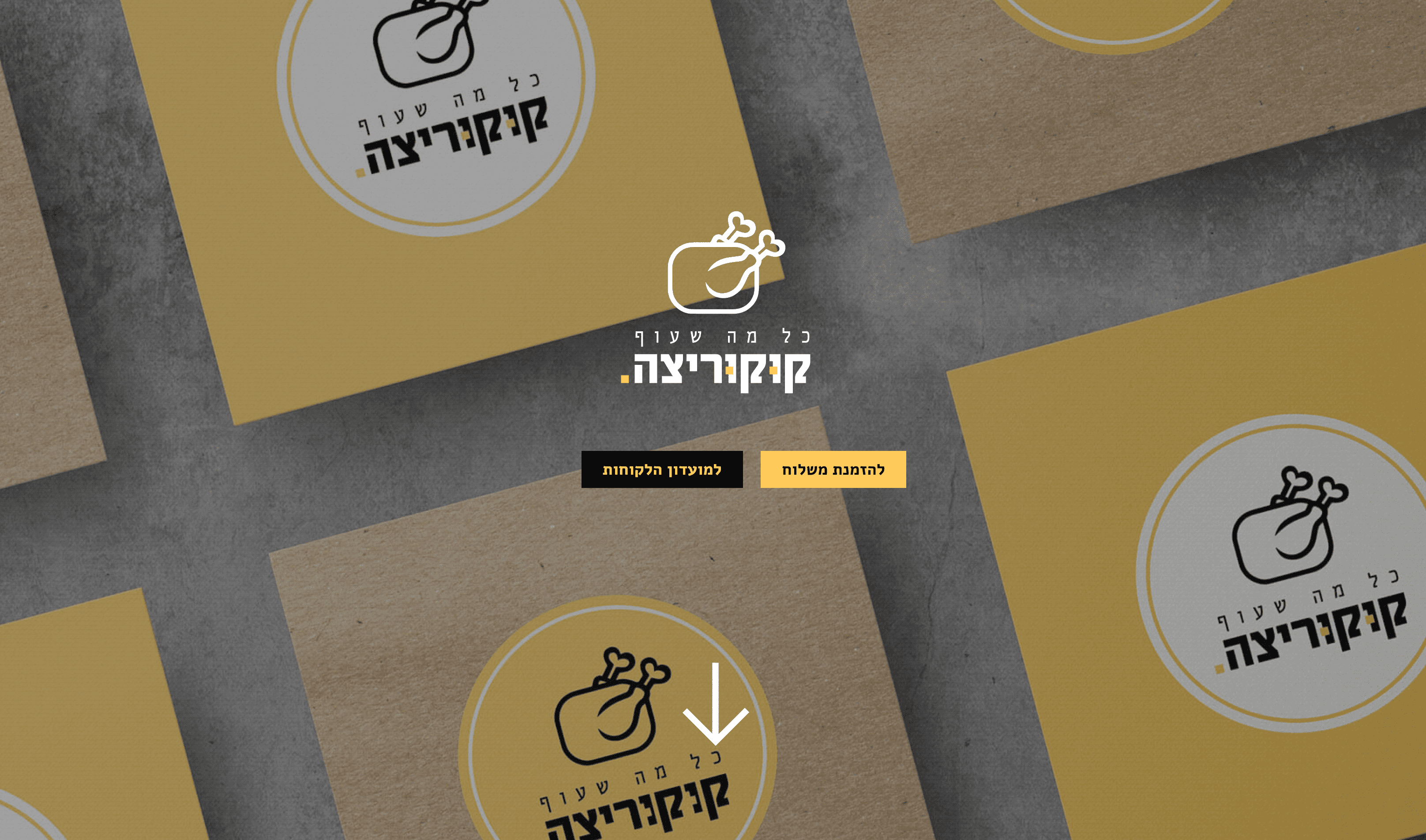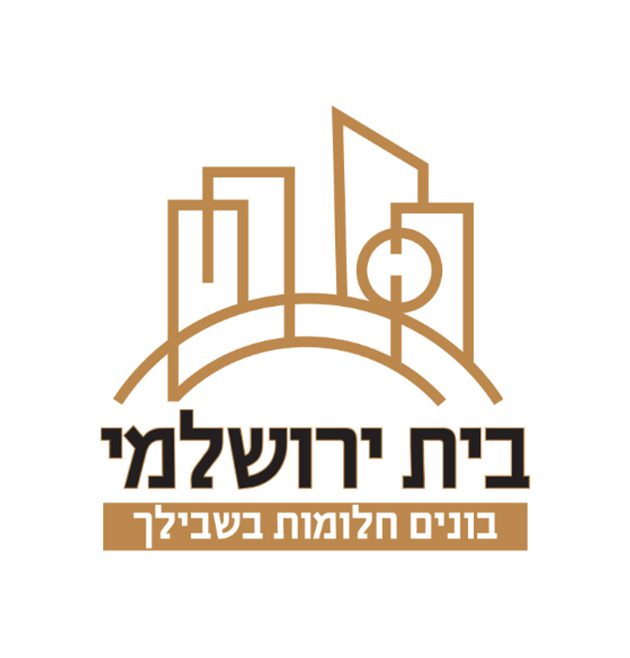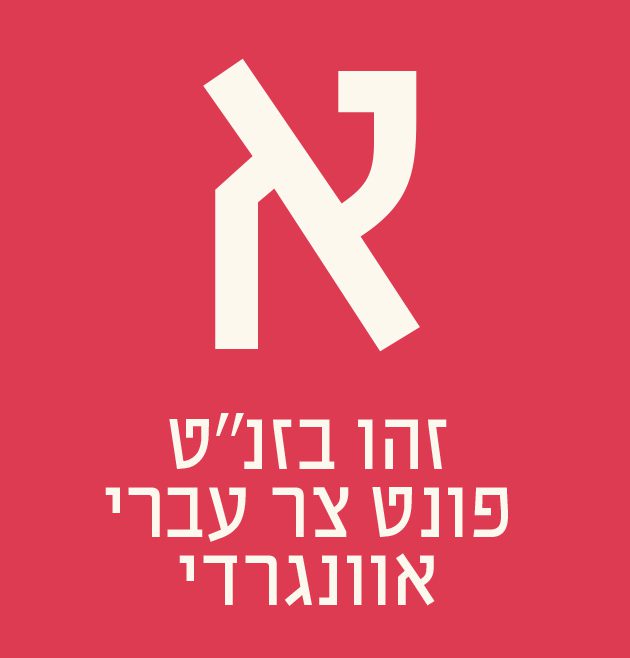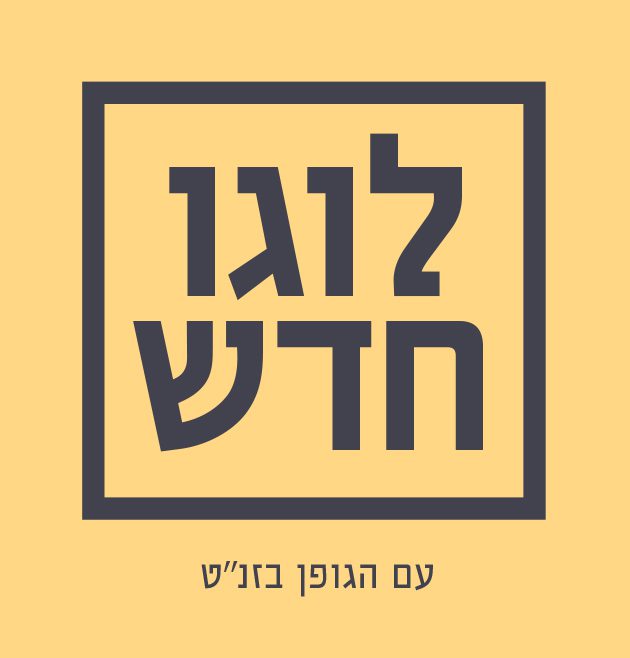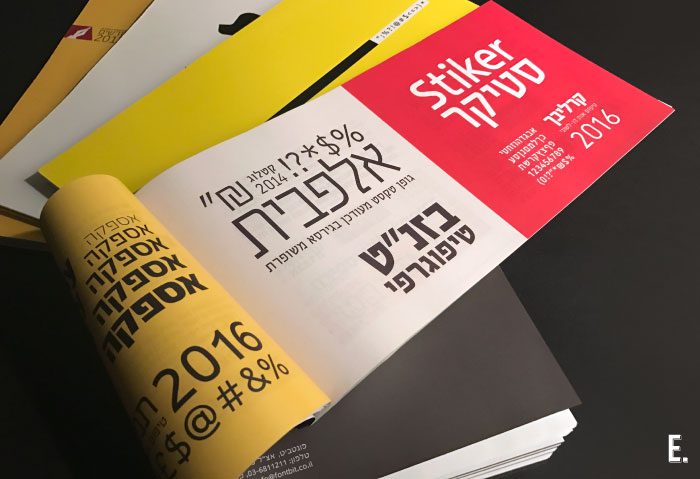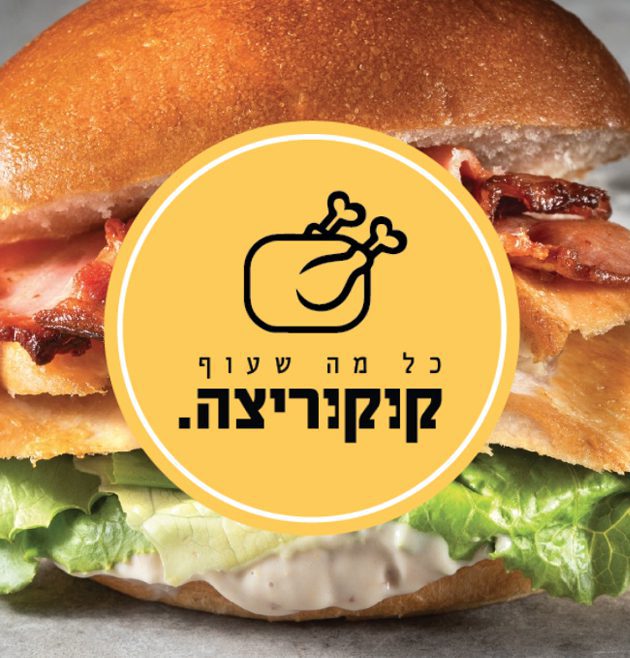
בזנ"ט
בזנ"ט / Baznat
• שם הגופן:בזנ"ט
• מעצב הגופן:נדב עזרא
• סגנון:סלאב סריף
• קטגוריה: עברית ראווה
• מאפיינים: קל רגיל כבד שחור
• תכונות: אוונגרדי מגזיני מודרני משולש עדין קוסמטי קשיח
סיפור הגופן:
פונט בזנ"ט, זהו טיפוס אות צר וזקוף הבנוי על מבנה גיאומטרי נוקשה ומשתייך לעולם והשפה הגרפית של פונטי כותרות ארכיטקטוניים. אבל בשונה מפונטים המשתייכים לז'אנר זה, פונט בזנ"ט מפתיע בתעוזה ובחוצפה הייחודית לו כפרשנות מרעננת וצעירה לאות העברית. טיפוס אות זה, מבטא את החיפוש אחר היחסים בין אות סנס סריפית לסאלב סריפית ונתמך במבנה מלבני גבוה (הפונט נגזר מתוך שלד האותיות שבפונט "טרפון").